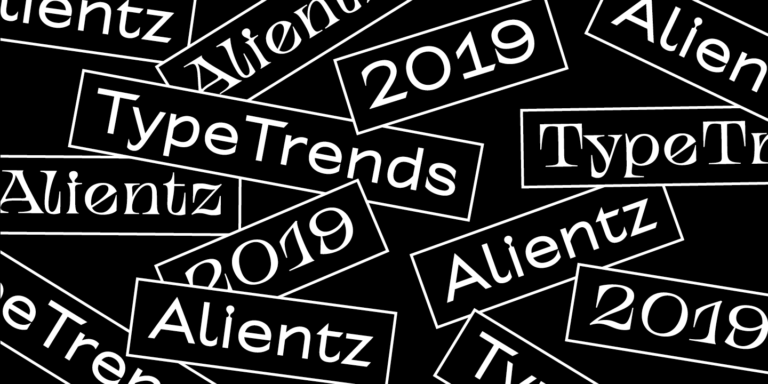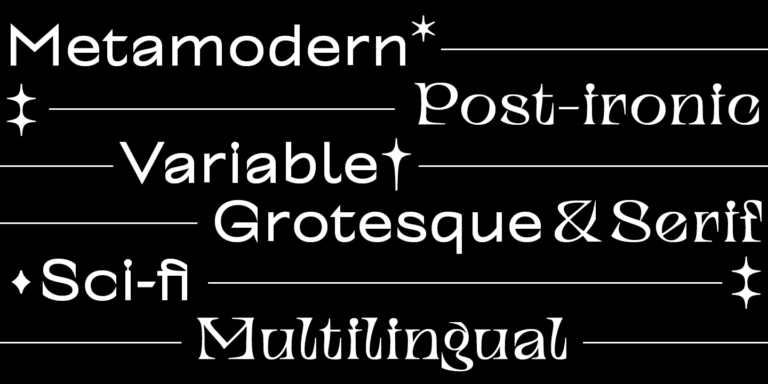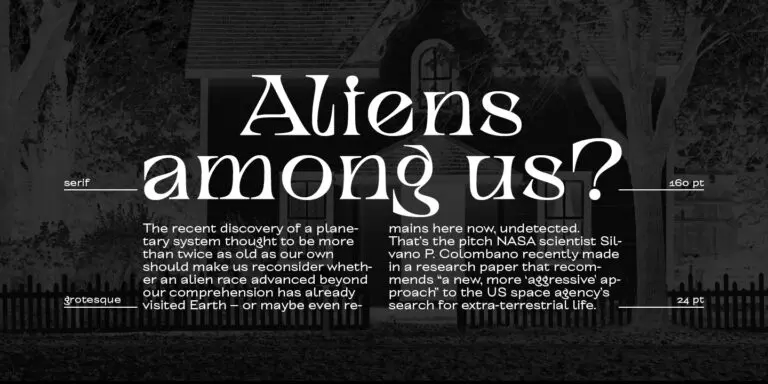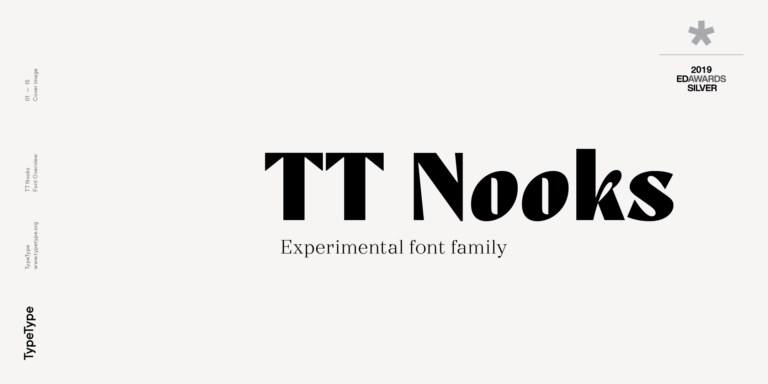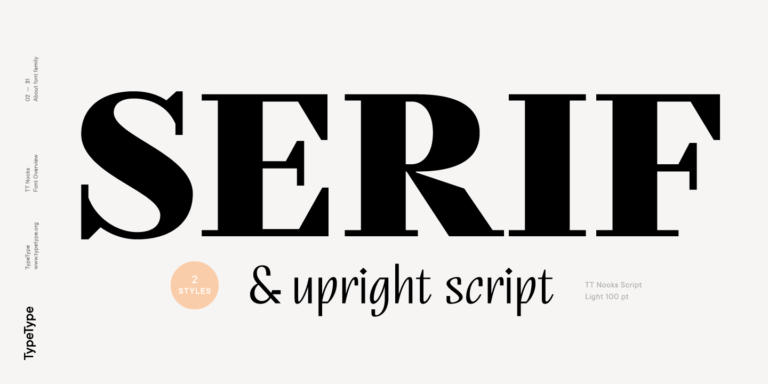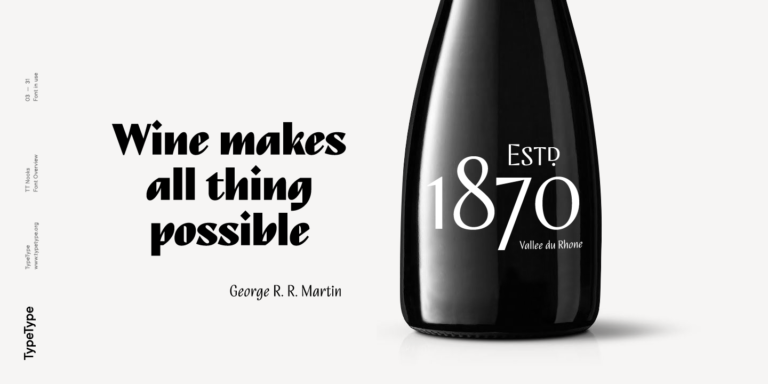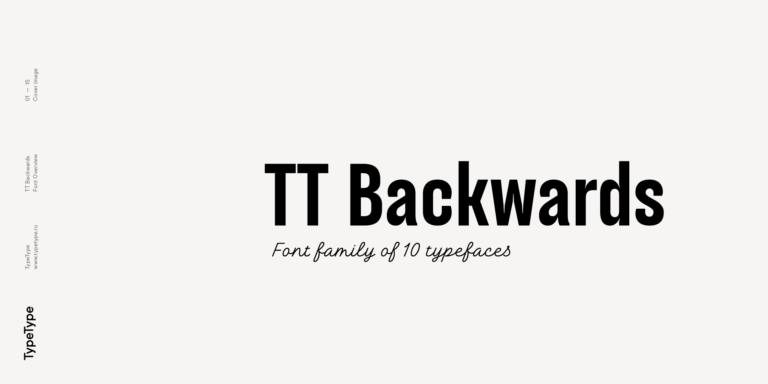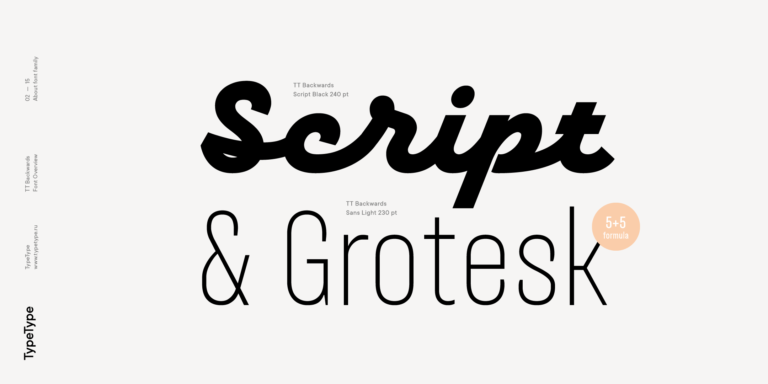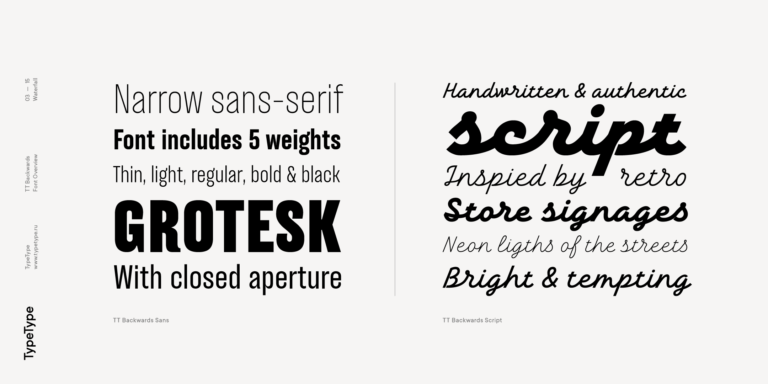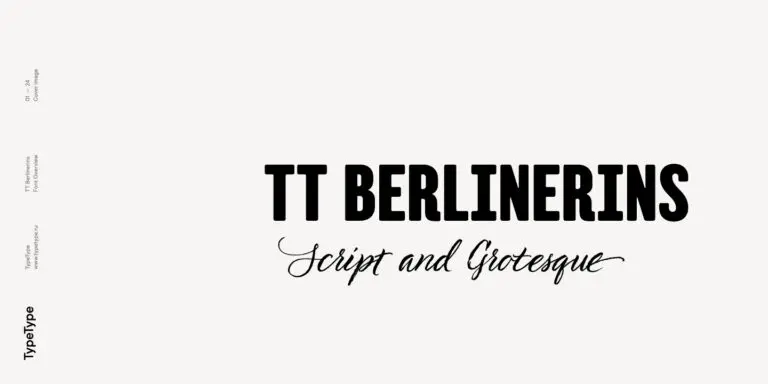
Die Auswahl der Tswana-Schriften
Wählen Sie eine geeignete Schriftart, die die Sprache Tswana unterstützt. Wir verfügen über eine umfangreiche Sammlung von Schriftfamilien, die allen kreativen Anforderungen gerecht werden, ob Sie nun an umfangreichen Textblöcken arbeiten, Überschriften für Websites oder gedruckte Publikationen entwerfen, auf verschiedene Materialien, einschließlich Stoff, drucken oder Schilder und Plakate entwerfen.
Jede der Schriftarten enthält das Tswana-Alphabet. Eine breite Palette von Zeichen, Währungs- und Interpunktionssymbolen, Schriftstilen und OpenType-Funktionen ermöglicht es Ihnen, dieselben Tswana-Schriften für verschiedene Projekte zu verwenden. Zeichen des erweiterten lateinischen Schriftsystems, die diakritische Zeichen enthalten, erweitern die Möglichkeiten, die Schriftart für jedes Land zu verwenden.
Jede Schriftart zeichnet sich durch eine einwandfreie technische Qualität aus. Viele Schriften in unserer Sammlung enthalten einen variablen Schriftstil, mit dem Sie einen einzigartigen Stil für Ihr Projekt schaffen können.
TT Livret ist eine elegante, moderne und funktionale Serifenschrift.
Die Schrift TT Chocolates besteht aus 14 Fonts: 7 Strichstärken und 7 Obliques. Sie bietet erweiterte Sprachunterstützung und nützliche Features.
TT Qurdisma ist eine schmale, kompakte dekorative Schrift, die an eine eigenwillige Pflanze erinnert. Ihre geschwungenen, fließenden Konturen bilden ein pflanzliches Ornament.
TT Dott ist eine experimentelle Pixel-Grotesk, die den Kreis zur Grundlage des Pixels macht. Sie ist eine plastische, ungewöhnliche Akzidenzschrift und weckt zugleich Assoziationen an Stickerei und Techno-Partys.
TT Rationalist ist eine funktionale und neutrale Slab-Serif-Schrift.
TT Commons™ Classic ist eine universelle Sans Serif mit minimalem Strichkontrast, geschlossener Apertur und geometrischen Zeichenformen.
TT Frantz ist eine experimentelle Variable Font, die sich durch ihre Schlankheit und Leichtigkeit auszeichnet. Die Variable beeinflusst die Höhe der Mittellinie: Durch Bewegen des Reglers lässt sich die Mittellinie der Schrift einfach anheben oder absenken.
TT Octosquares ist eine frische, überarbeitete, erweiterte und deutlich verbesserte Version unserer ersten kommerziellen Schrift TT Squares und ihrer schmalen Variante.
Eine technologische Schriftfamilie für Game Design.
TT Bluescreens ist eine verbesserte geometrische Sans Serif mit schmalen Proportionen.
TT Rounds Neue ist eine weiche, freundliche und abgerundete Sans-Serif-Schriftfamilie.
TT Norms® Pro ist eine typografische Legende, die von weltbekannten Marken geschätzt wird. Entwickelt durch mehrere Iterationen, hat sie MyFonts erobert und typografische Vielseitigkeit neu definiert. Ein Design-Arbeitspferd, das sich von einem bescheidenen Werkzeug in einen unverzichtbaren kreativen Begleiter verwandelt.
TT Commons™ Pro ist das typografische Kraftpaket des Studios. Eine Schriftart, die so vielseitig ist, dass sie sich einer Kategorisierung entzieht und Stil und Funktion nahtlos verbindet. Für Designer, die eine universelle Grundlage suchen, die jedes Projekt aufwertet, ist dies die endgültige Wahl.
TT Hoves Pro ist eine skandinavische serifenlose Schrift, die minimalistische Eleganz versprüht. Sie ist die Geheimwaffe eines Designers, der komplexe Herausforderungen mit müheloser Präzision in visuelle Poesie umwandelt, und dabei gleichzeitig dezent und unverwechselbar.
TT Supermolot Neue verändert die visuelle Kommunikation grundlegend! Eine fortschrittliche, modulare serifenlose Schrift, die den Puls der technologischen Innovation einfängt und eine elektrisierende Vision für alles von immersiven Spieloberflächen bis hin zu kühnen visuellen Erzählungen bietet.
TT Knickerbockers Grotesk ist eine schmale kontrastreiche Grotesk mit charakteristischen Elementen, die an das New York des 19. Jahrhunderts erinnern.
TT Polls ist eine moderne modulare Slab-Serif-Familie für den Einsatz im Sportdesign.
TT Berlinerins ist eine Grotesk, inspiriert von Holzlettern auf Plakaten aus dem ersten Drittel des 20. Jahrhunderts, und bringt die historische Komponente Berlins zum Ausdruck.